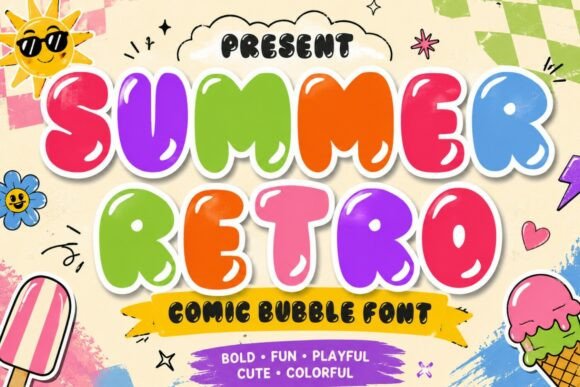
Summer Retro
Att hitta rätt designelement kan vara utmanande, men Summer Retro erbjuder en exceptionell samling som omedelbart lyfter ditt arbete.
Oavsett om du skapar POD-produkter (Print on Demand), bröllopsinbjudningar eller grafik för sociala medier, är Summer Retro ett perfekt val.